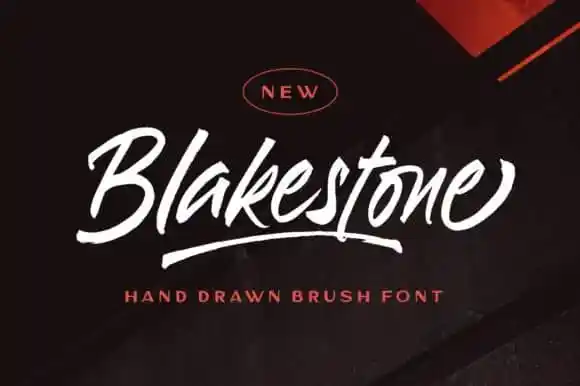
Blakestone Brush Font – Download Grátis
A Blakestone Brush Font é uma tipografia feita para quem busca uma sensação amigável e vibrante em seus designs digitais. Com seu estilo livremente inspirado no desenho a mão com um pincel, ela traz um toque de felicidade aos projetos que utiliza. Esta fonte foi criada para aqueles que valorizam a essência dos tempos livres e do processo creativo. É perfeita para criar visuais divertidos e únicos, seja em cartazes ou em design gráfico digital, tornando seus trabalhos ainda mais vivos. A Blakestone Brush Font é uma escolha inteligente para aqueles que desejam dar um toque personalizado às suas criações, com um charme único de letra a mão. Seja você designer web, publicitário ou qualquer outro campo relacionado à comunicação visual, esta fonte certamente ajudará a destacar seus projetos e trazer um ar descontraído aos seus trabalhos.